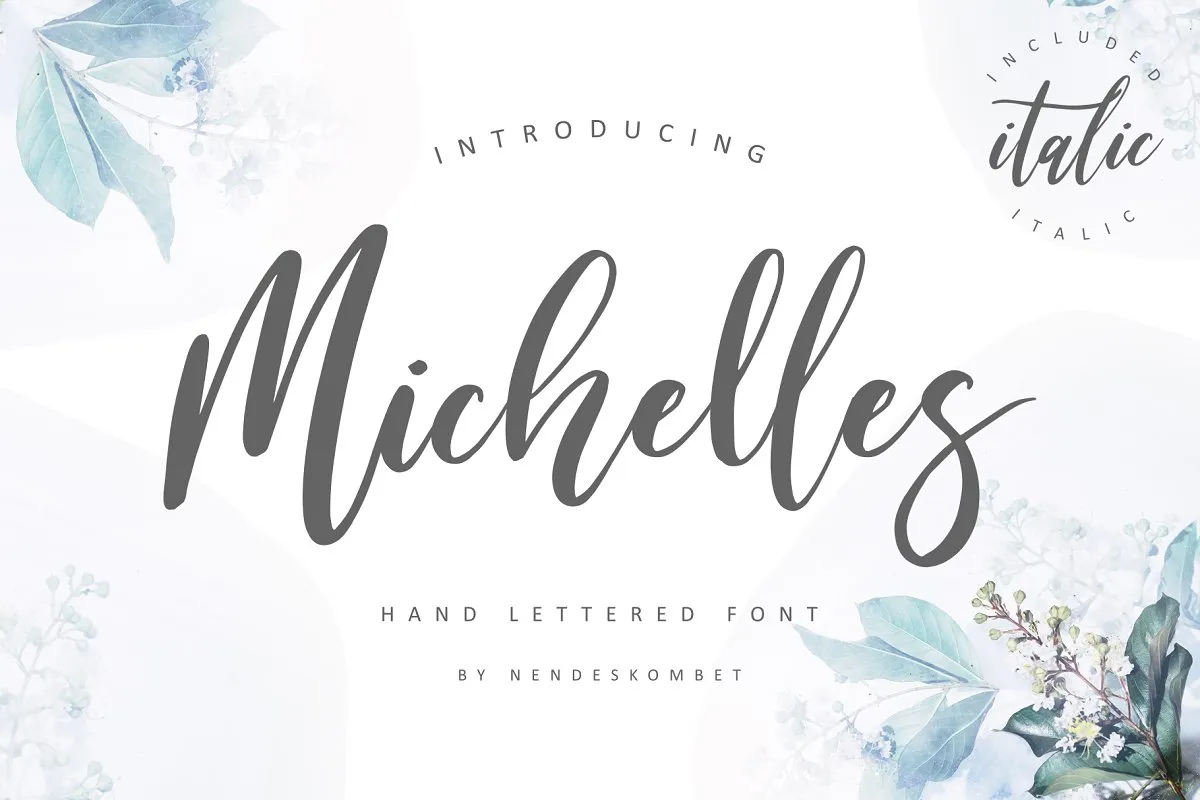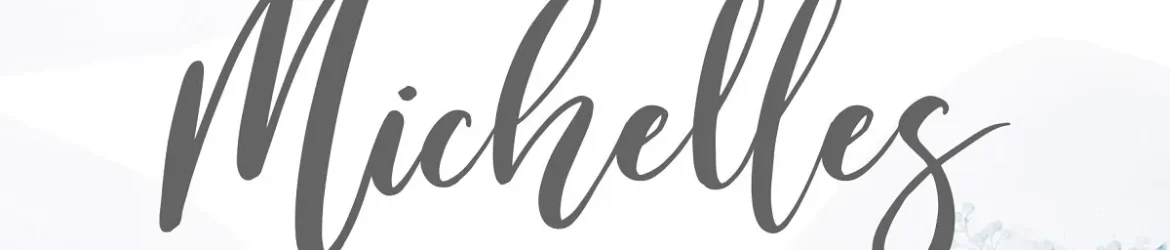
Michelles Script Font – Download Grátis
A Michelles Script Font é uma nova fonte com estilo calligráfico que se destaca pela sua elegância e energia inebriante. Desenvolvida para designers de logomarcas, impressões personalizadas e embalagens, essa fonte criativa pode transformar qualquer texto em uma obra-prima delicada e imponente. Com apenas um clique, você poderá criar texturas únicas e cheias de personalidade que se destacam do resto da página. Essa fonte é perfeita para ilustrações de cartões, selos de produto e design de cabeçalhos, permitindo-lhe explorar criativamente a linguagem visual de um projeto. Sem dúvida, ela será o ponto focal perfeito para qualquer layout gráfico que você criar.